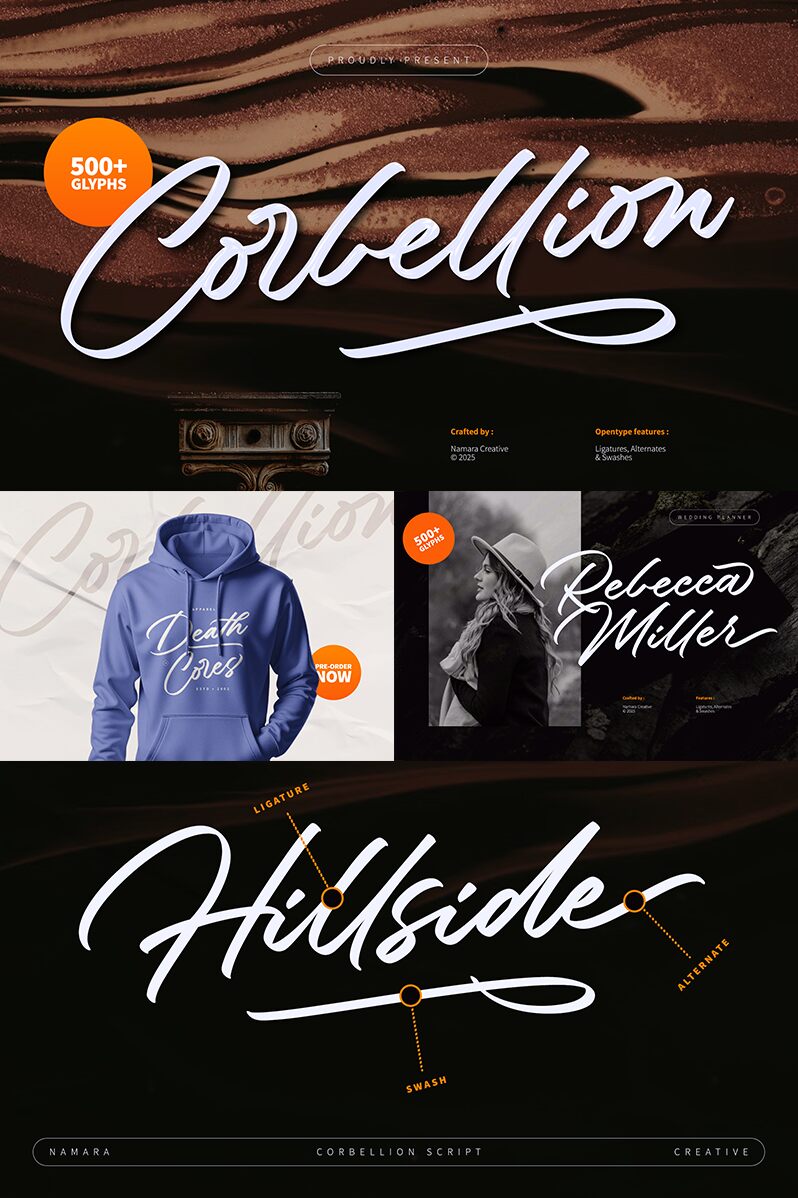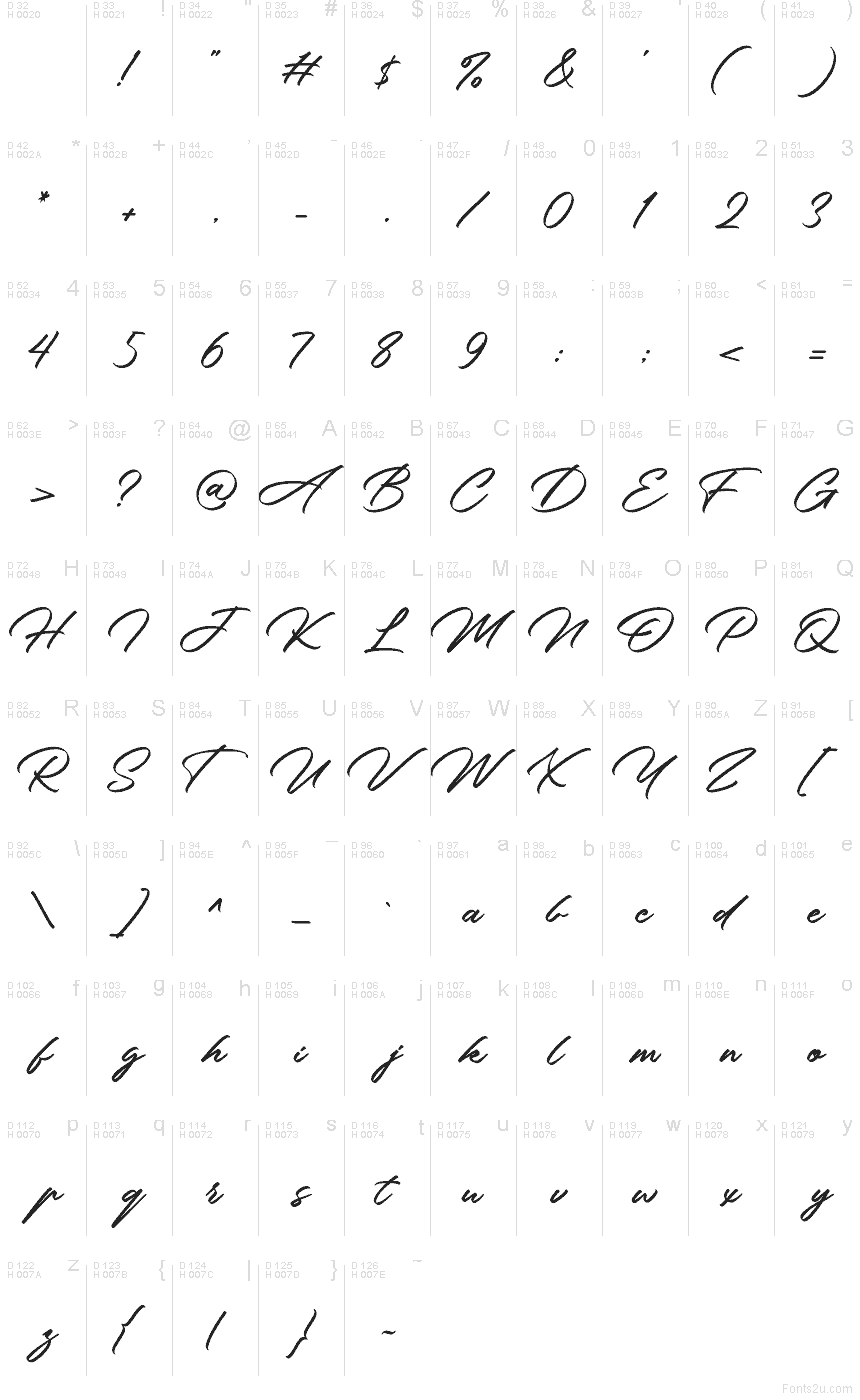
Corbellion od Namara Creative je bezplatné psací písmo definované rozmáchlým kurzivním rytmem a dramaticky velkou počáteční smyčkou, která udává tempo zbytku znaků. Tahy zůstávají hladké a plynulé, zatímco se zužují do rychlých obratů a kompaktních spojů, což dodává tomuto písmu sebevědomý nádech podpisu namísto ležérního stylu štětce.
Díky tomuto pohybu je Corbellion silnou volbou pro loga, obaly, nadpisy pozvánek, citáty na sociálních sítích a branding v oblasti krásy nebo módy, kde musí jediný řádek působit osobně a vyváženě. Písmo se také skvěle hodí na etikety produktů a značení butiků, zejména když tento široký počáteční prvek dokáže zarámovat krátký název nebo titulek.